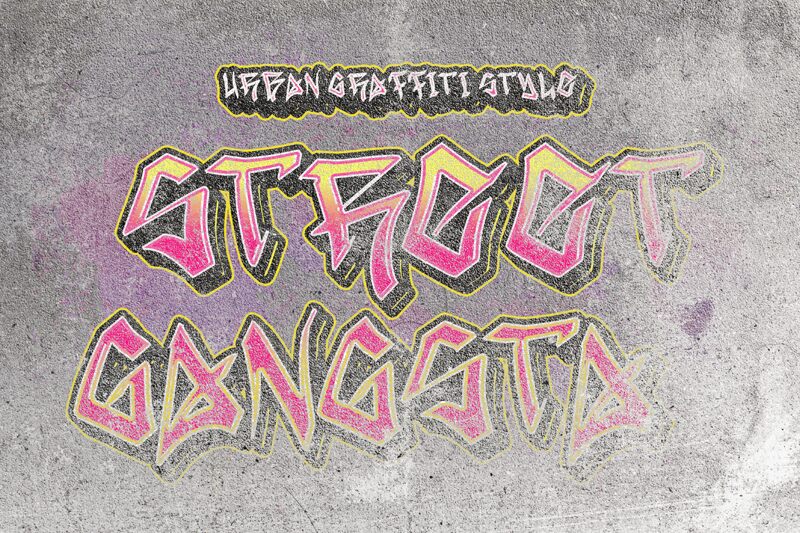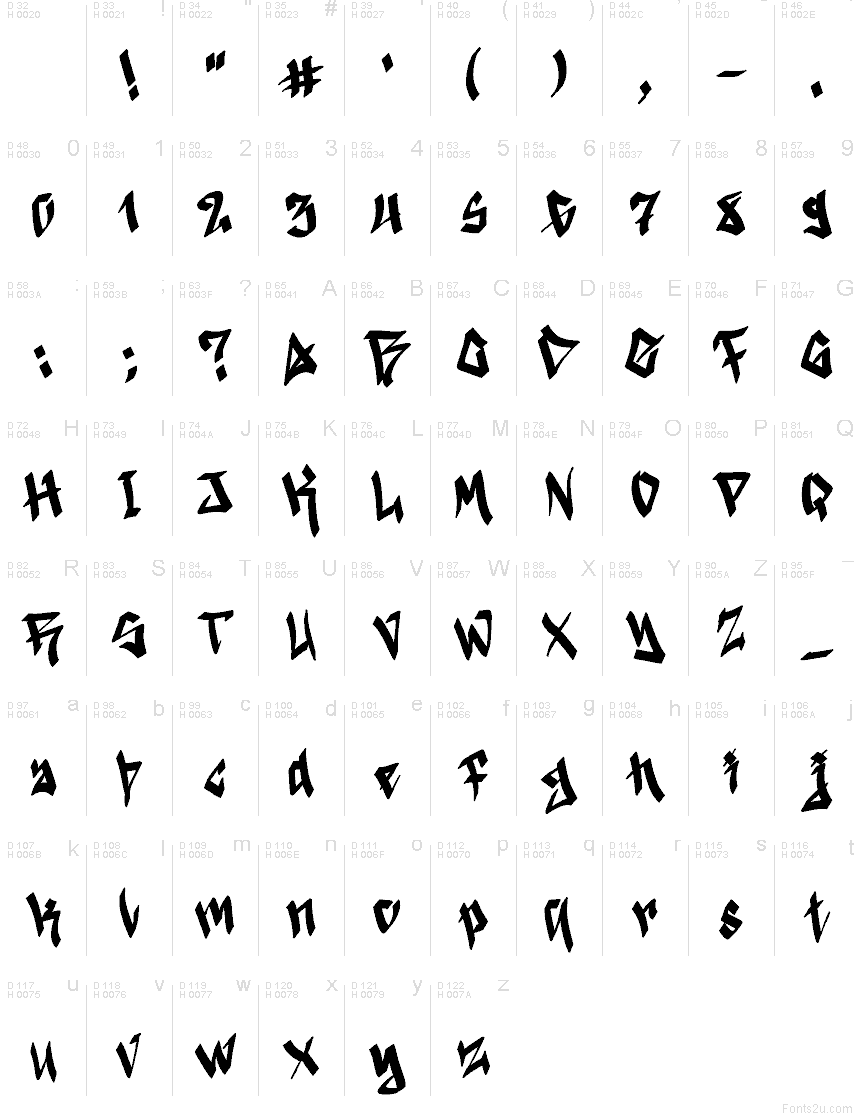
Street Gangsta Demo
Street Gangsta é uma fonte de grafite gratuita com traços afiados e angulares, inspirada nas formas dos tags de rua. As letras são moldadas em ângulos pontiagudos e cortes irregulares, conferindo ao design um ritmo manuscrito cru que parece ter saído diretamente da arte urbana.
Street Gangsta funciona muito bem em títulos de pôsteres, flyers musicais, gráficos de skate, estampas de vestuário e branding urbano, onde um estilo de tag autêntico se encaixa perfeitamente. Esta fonte gratuita também é ideal para logotipos, artes para redes sociais e sinalização de eventos impactante, pois suas formas irregulares carregam um forte caráter manuscrito sem a necessidade de ornamentos adicionais.